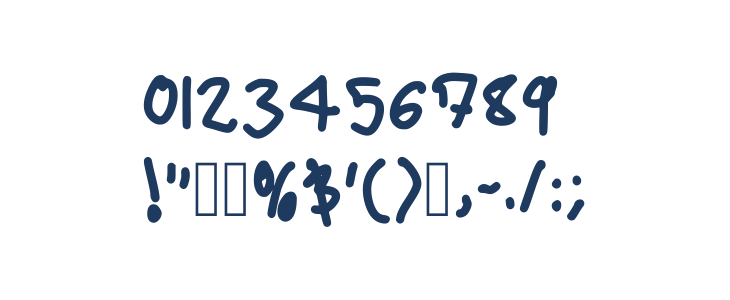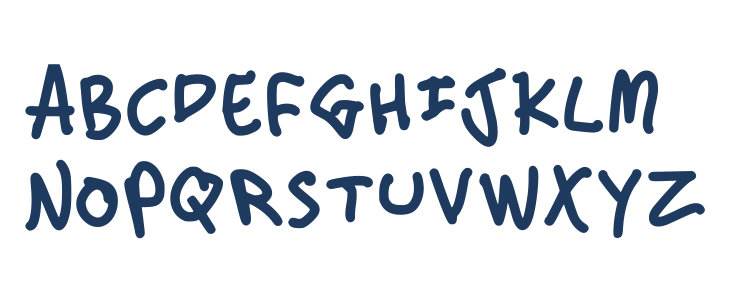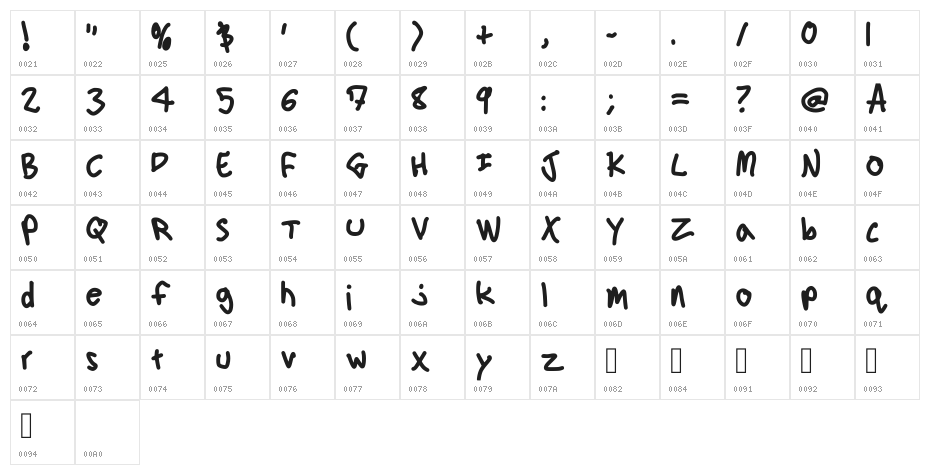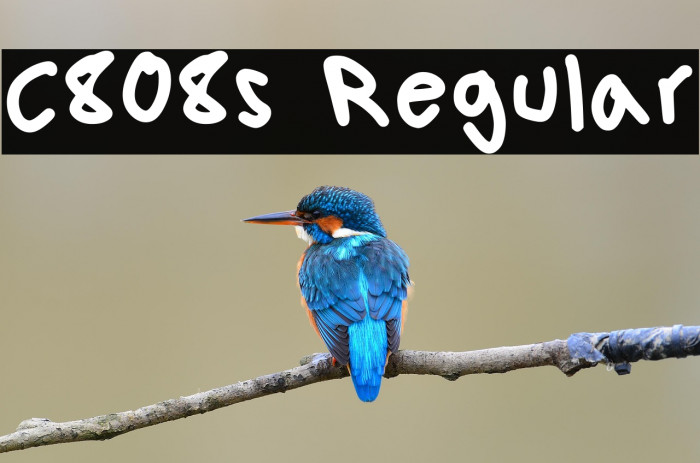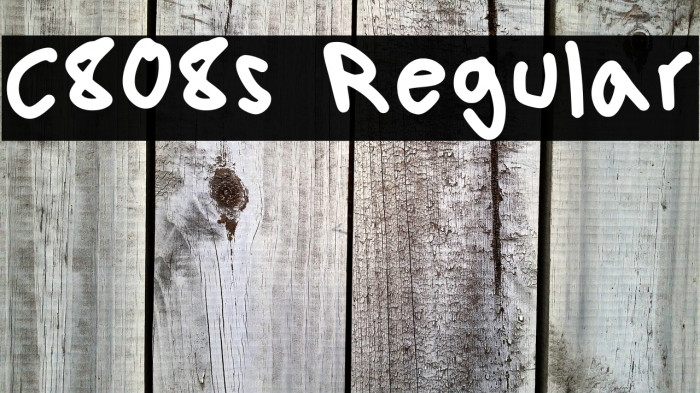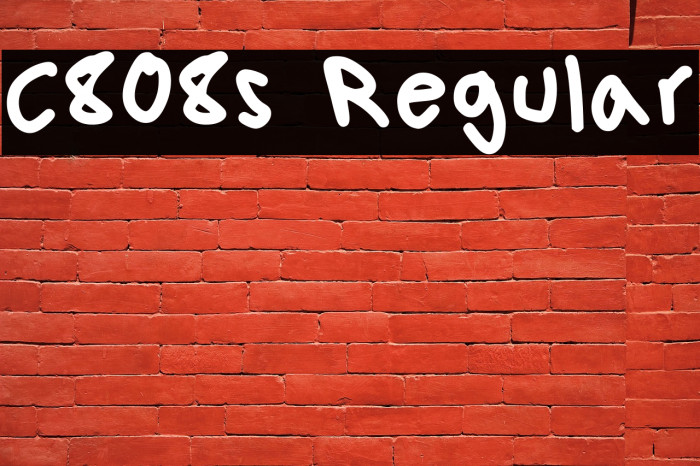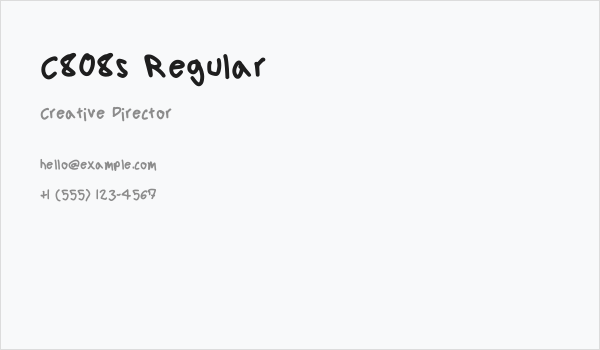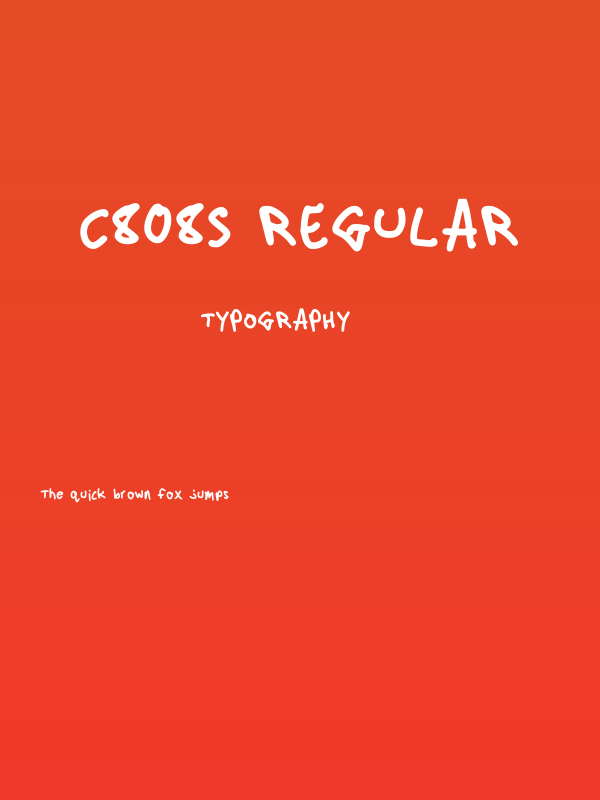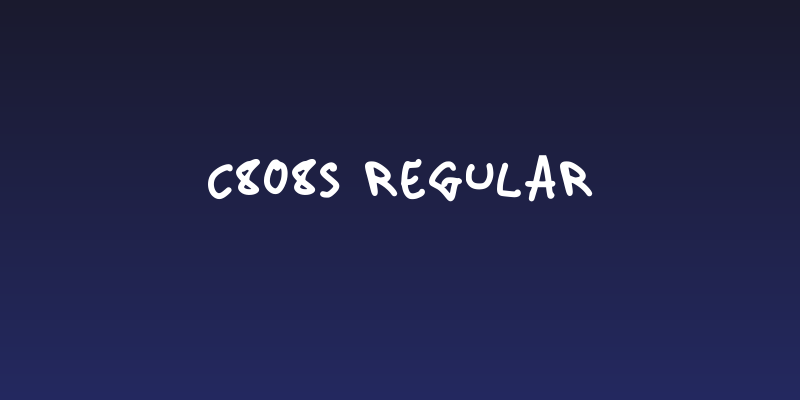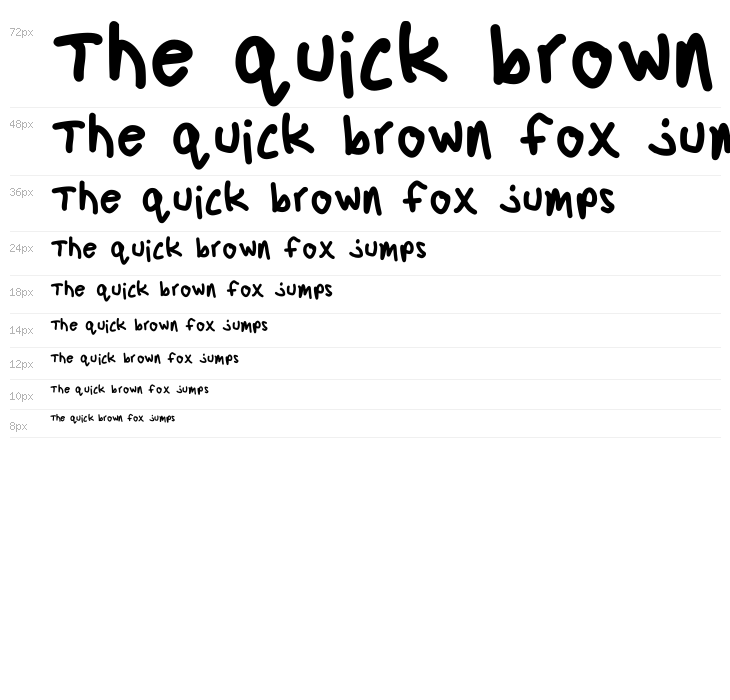
C808s Regular Font
| Stile generale | Playful, Casual, Handwritten |
| Caso d'uso | Headlines, Posters, Informal notes, Branding |
| Progetti proposti | Children’s books, greeting cards, posters, casual branding, educational materials. |